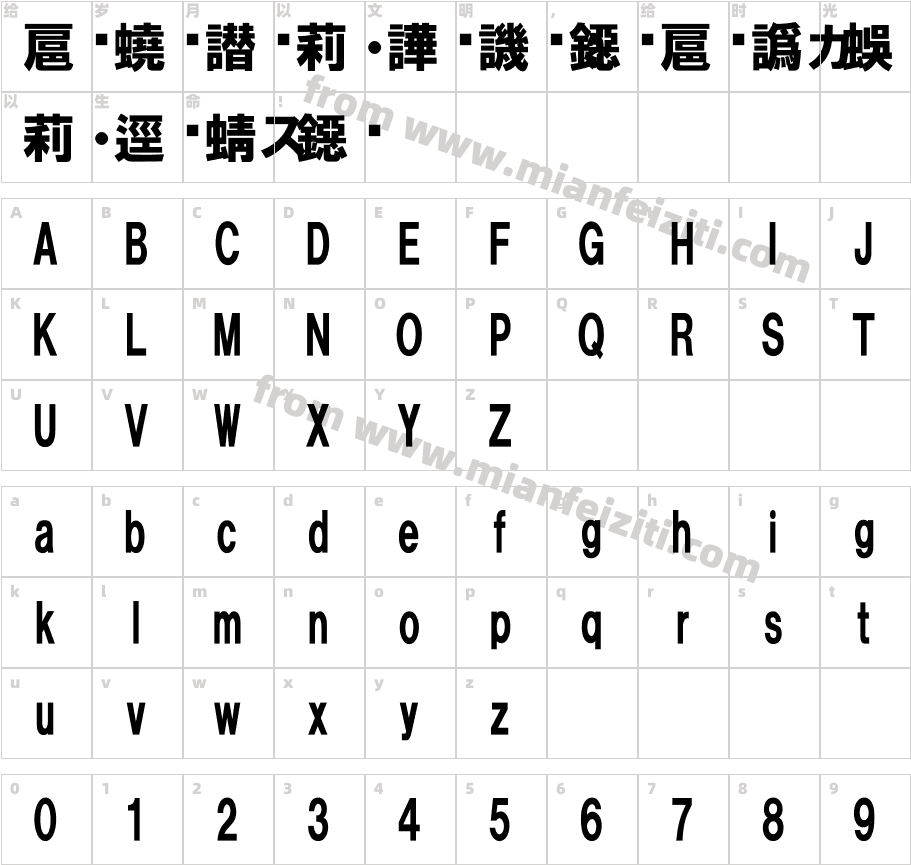
HG創英角UB
字体名称: HG創英角UB
Postscript名称: HGSoeiKakugothicUB
字体版本: Ver.1.51 (c256-sguh10-sguz10-j0kei10-sguf10-sgus10-sgun10-sgue10-sguv11-vkei10)
字体字重: ウルトラボールド